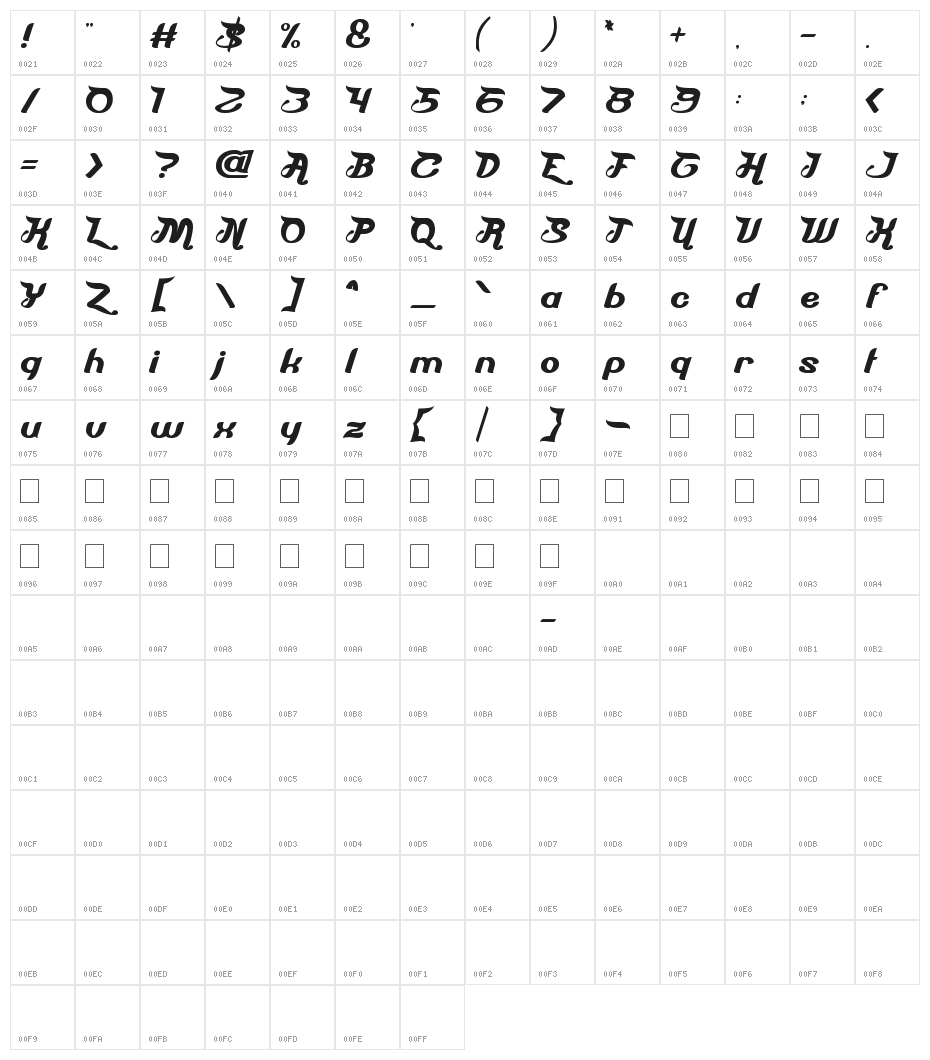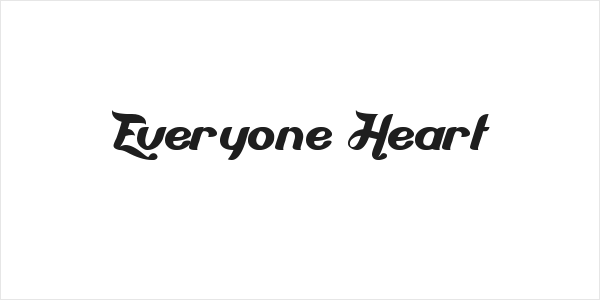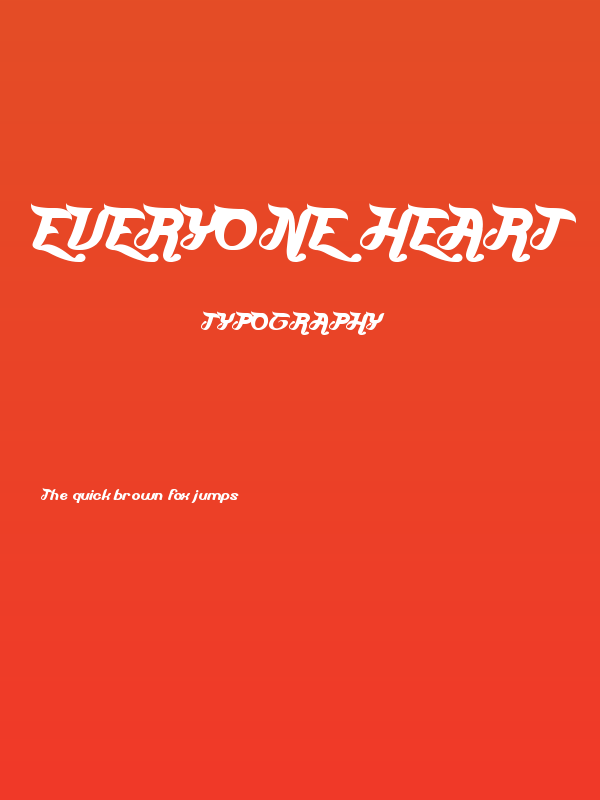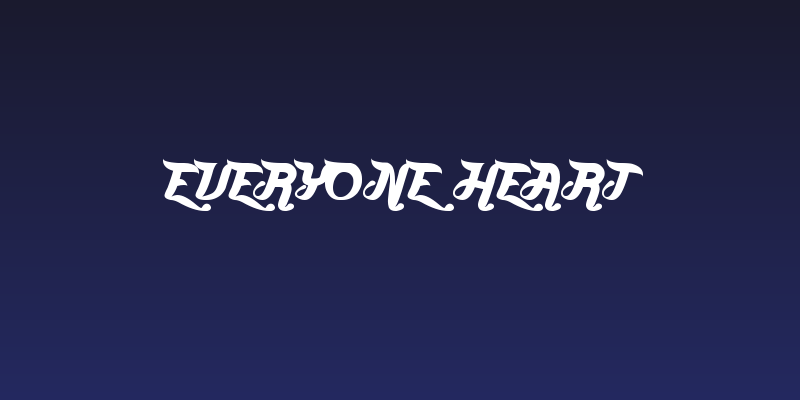
Everyone Heart Font
| Caso d'uso | Logos, Headlines, Artistic projects |
| Progetti proposti | Ideal for wedding invitations, greeting cards, branding projects, and artistic posters. |